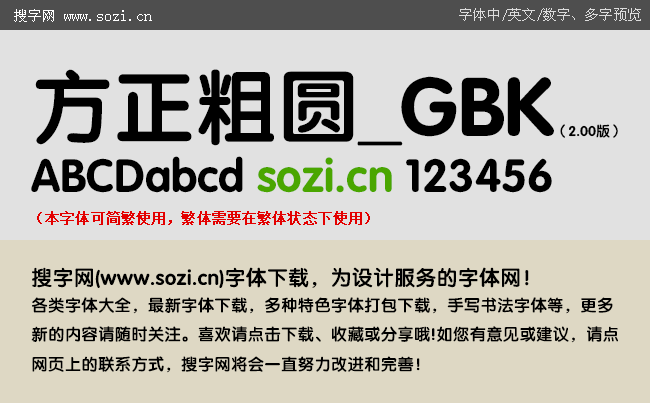
方正粗圓_GBK
搜字網(wǎng)提供一款方正粗圓_GBK中文字體下載,方正粗圓是一款非常端正的中文字體,適合在正式的場(chǎng)合來(lái)進(jìn)行使用,GBK編碼收字更全,適合應(yīng)用于廣告設(shè)計(jì)、名片設(shè)計(jì)、包裝印刷、產(chǎn)品設(shè)計(jì)等應(yīng)用。